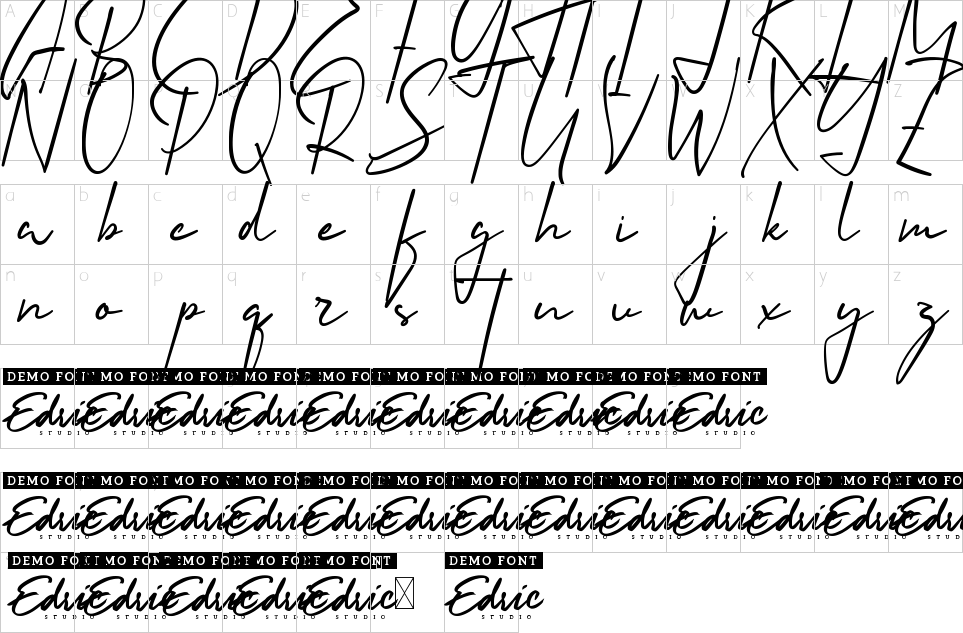
A fonte Photo Journalist é uma escolha inteligente para jornalistas fotográficos, designers de sites e qualquer pessoa que precisa de uma fonte capaz de ressaltar sua mensagem de forma clara e poderosa. Desenvolvida por EdricStudio, esta fonte foi projetada para quem busca uma maneira eficaz de destacar suas imagens através de textos. Com sua aparência moderna e clean, a Photo Journalist fornece um tom atraente que transmite profissionalismo e eficiência. Descarregada milhares de vezes, a font Photo Journalist é uma escolha confiável para aqueles que querem adicionar um toque de qualidade à sua documentação visual. Com a Photo Journalist, você pode criar textos que são tanto impactantes quanto elegantes, aperfeiçoados para combinar perfeitamente com as imagens e notícias que estão sendo compartilhadas. Seja você um jornalista, um publicitário ou uma pessoa que valoriza a importância de uma boa fonte, Photo Journalist pode ser a solução perfeita para sua necessidade.